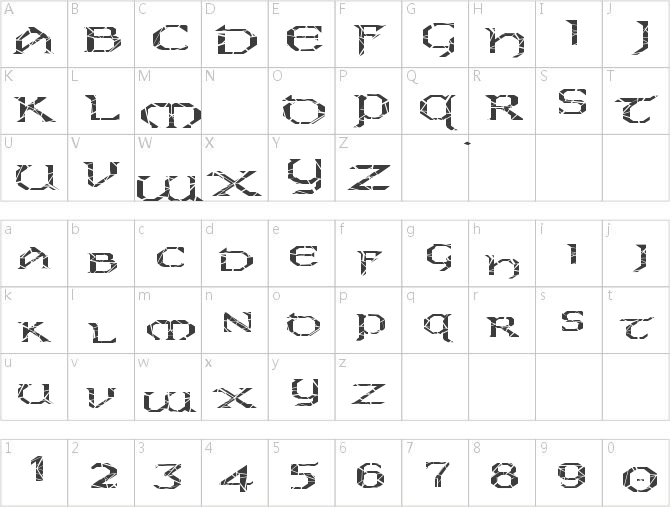
FZ JAZZY 31 CRACKED EX 詳情頁(yè)
FZ JAZZY 31 CRACKED EX字體字庫(kù)是一款讓人賞心悅目、百看不厭的英文字體,適合各類(lèi)廣告和產(chǎn)品包裝設(shè)計(jì)應(yīng)用,字體大小0.1MB,格式為ttf字體,上傳用戶(hù)是翰池書(shū)法,作者/版權(quán)方為未知